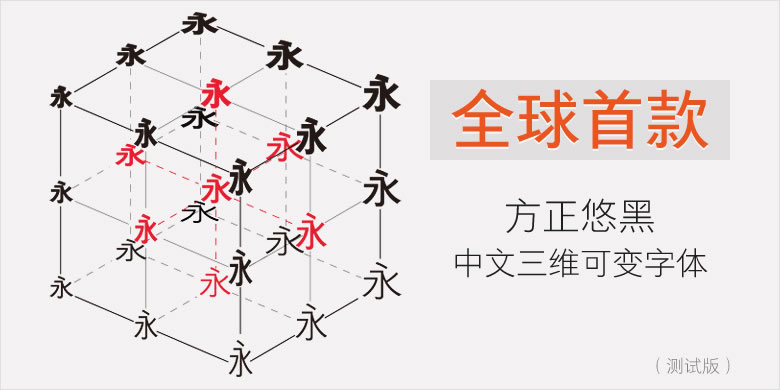
方正悠黑简三维可变
OpenType可变字体是一种等同于多个单独字体的一种字体,它可以紧凑地封装在单个字体文件中。可变字体是一个单一字体文件,但是其行为类似于多种字体。
由于中文字形和西文字形存在很大差异,字符集较大,字形复杂,目前中文字库维度变化主要在weight、width和height三个轴,未来考虑增加其它轴,如重心、中宫、笔画粗细对比度等等。目前方正字库实现了一维可变、二维可变、三维可变,即可以包含一个轴、两个轴、三个轴,且可变字库中每个轴至少需要两档字形数据,提供字体设计的不同极端之间的特定变化。同时还允许在每个轴上添加中间档数据,增加对于整个字形集或针对单个字形的中间设计的可能性,以便在变化设计空间上变化时对设计提供更精细的控制。
方正悠黑三维可变字库具有weight(字重)、width(字宽)和height(字高)轴的三轴可变字体的设计空间。